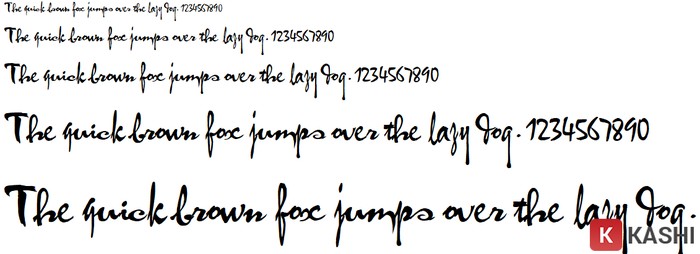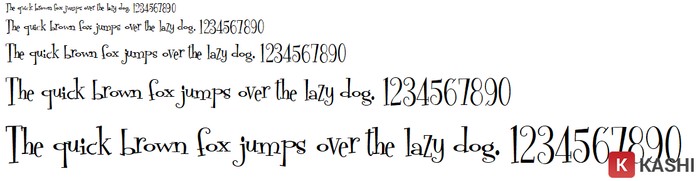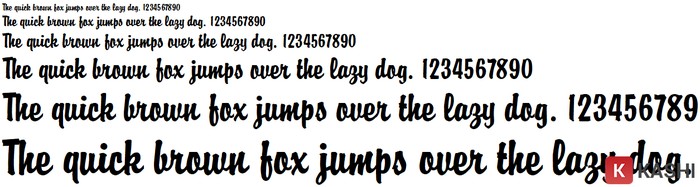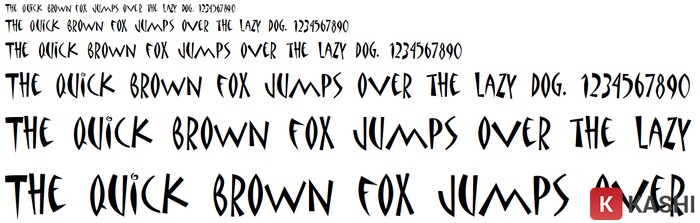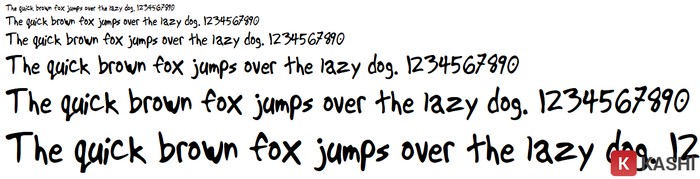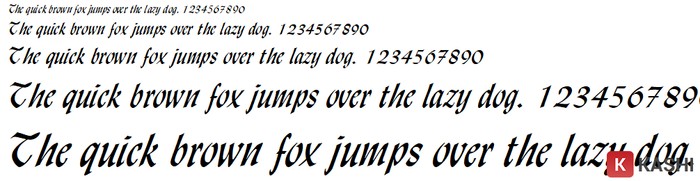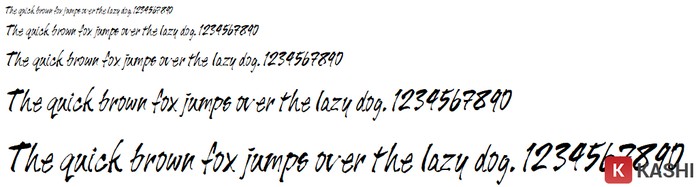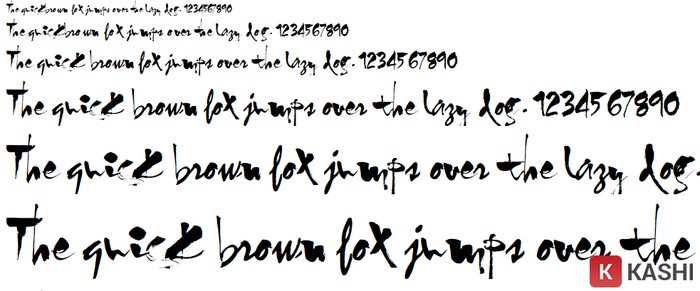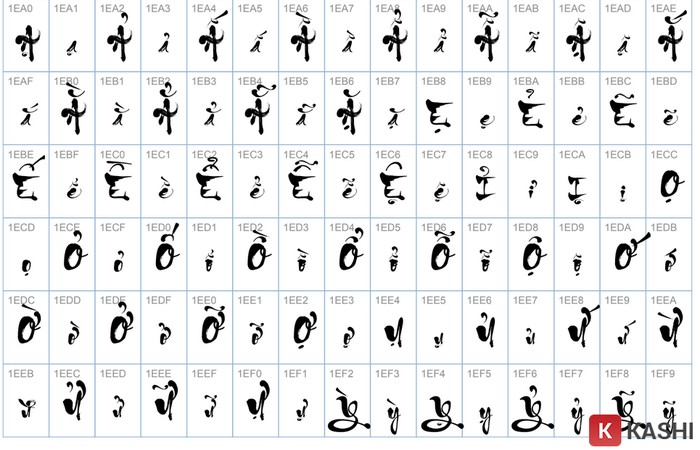
Font chữ thư pháp, một nét đẹp văn hóa truyền thống của Việt Nam, đặc biệt được ưa chuộng trong dịp Tết. Không còn phải chờ đợi ông đồ như xưa, giờ đây bất kỳ ai cũng có thể tự tạo ra những câu đối, thiệp chúc Tết với những mẫu chữ thư pháp độc đáo. Bài viết này sẽ giới thiệu đến bạn đọc những font chữ thư pháp đẹp nhất 2025 và hướng dẫn cài đặt chi tiết.
Font Chữ Thư Pháp Là Gì?
Font chữ thư pháp là kiểu chữ được viết theo phong cách nghệ thuật độc đáo, mang đậm tính thẩm mỹ. Là một nét văn hóa lâu đời của người Việt, font chữ thư pháp thường xuất hiện trên câu đối, thiệp chúc Tết, trang trí bánh chưng, dưa hấu…
Tuy nhiên, do yêu cầu sự tỉ mỉ và khéo léo, việc viết chữ thư pháp truyền thống khá cầu kỳ. Ngày nay, với sự phát triển của công nghệ, font chữ thư pháp kỹ thuật số ra đời, giúp việc tạo ra những tác phẩm mang đậm nét văn hóa truyền thống trở nên dễ dàng hơn.
Phân Loại Font Chữ Thư Pháp
Font chữ thư pháp được chia thành hai loại chính:
• Văn bản: Thường dùng trong thiệp mời, bằng khen, giấy khen… để tăng tính trang trọng. Khác với các font chữ thông thường, font chữ thư pháp mang lại sự độc đáo, không bị đại trà, thường được sử dụng trong các dịp lễ, Tết.
• Tranh chữ (thư họa): Là những bức tranh được tạo thành từ nhiều chữ thư pháp, mỗi chữ thường có kích thước lớn và mang nội dung súc tích. Mỗi nét chữ không chỉ thể hiện ý nghĩa của từ mà còn toát lên vẻ đẹp nghệ thuật. Tranh chữ thường được dùng để trang trí nhà cửa với các câu chúc, câu đối ý nghĩa.
Tính Năng Của Font Chữ Thư Pháp
Font chữ thư pháp thường được ứng dụng trong thiết kế thiệp, banner, poster, đặc biệt là trong các dịp lễ, Tết. Mỗi nét chữ thư pháp đều mang đậm tính nghệ thuật, thể hiện tâm tình của người viết. Với nhiều phong cách đa dạng, font chữ thư pháp có thể được sử dụng để tạo ra các câu ca dao, tục ngữ, hay tô điểm cho các bức bích họa.
Tổng Hợp Font Chữ Thư Pháp Đẹp Nhất 2025
Dưới đây là một số font chữ thư pháp đẹp và được ứng dụng nhiều nhất trong năm 2025:
1. TMC-Ong Do: Mẫu chữ thư pháp ấn tượng
2. HL Thuphap 2BK: Mẫu chữ thư pháp truyền thống
3. HL Thanhcao: Mẫu chữ thư pháp sáng tạo
4. UVN Co Dien: Mẫu chữ thư pháp độc đáo
5. UVN Moi Hong: Mẫu chữ thư pháp đơn giản
6. VNI-Briquet Normal: Mẫu chữ thư pháp tinh tế
7. VNI-Matisse: Mẫu chữ thư pháp độc đáo
8. VNI-Viettay Normal: Mẫu chữ thư pháp nguệch ngoạc
9. UVN Ly Do: Mẫu chữ thư pháp nét thanh nét đậm
10. UVN Muc Cham: Font chữ thư pháp cách điệu